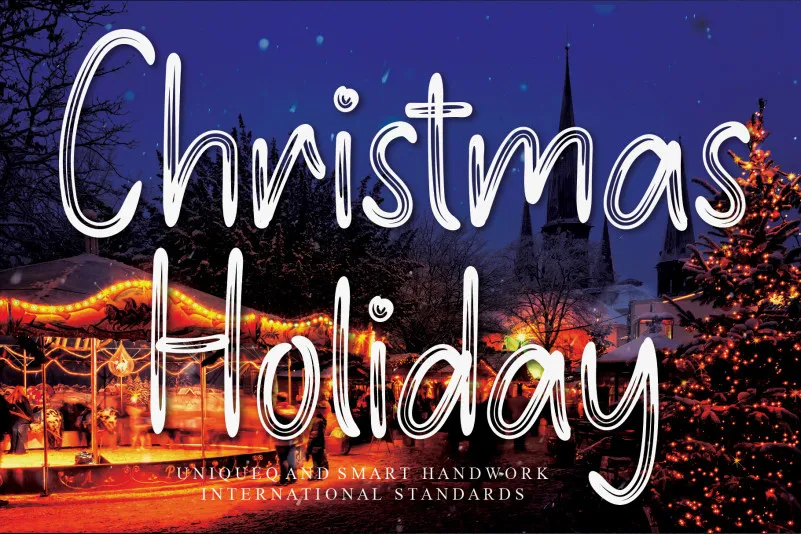
Christmas Holiday Brush Font – Download Grátis
A fonte ‘Christmas Holiday Brush Font’ é uma elegante fonte escrita à mão que transmite leveza e amizade. Perfeita para decorar convites natalinos, cartas de Natal, mensagens personalizadas e cartões festivos. Seu tom suave e encantador torna-a ideal não apenas para elementos da arte natalina, mas também para a criação de logotipos ou cards comerciais onde um toque autêntico dos dias de hoje seja especialmente valorizado. Com ‘Christmas Holiday Brush Font’, você pode adicionar uma pitada de charme ao seu design sem comprometer o estilo moderno que é tão valorizado em nosso mundo digital.